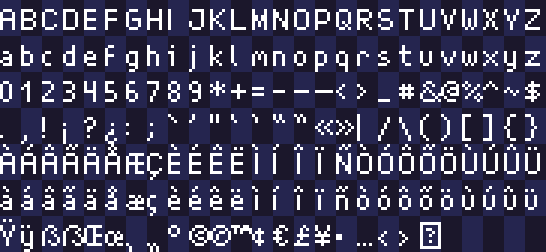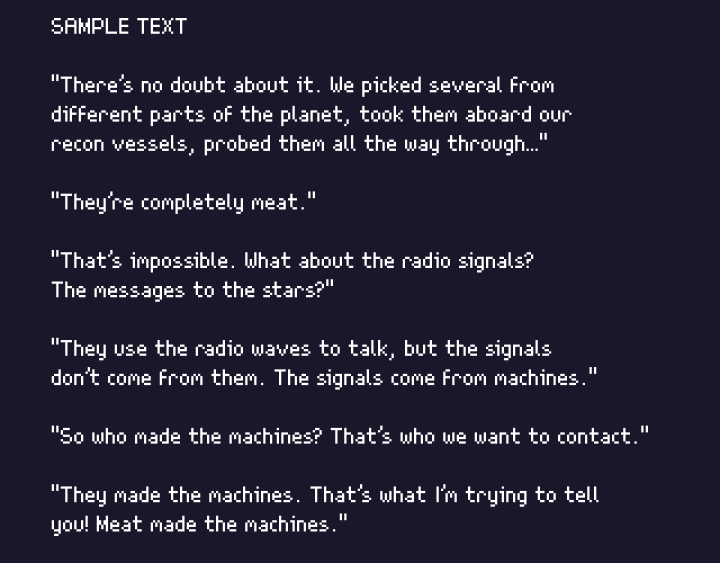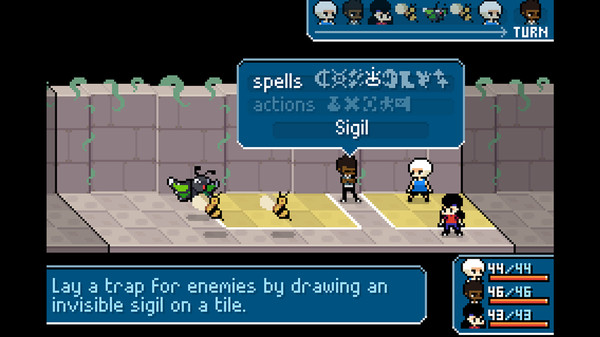
小巧简洁的Supersoft像素字体素材,专为像素艺术游戏而设计,易于阅读。这款字体可用于商业和非商业游戏、视频、直播叠加层、网站等等!
该字体支持以下所有字符:
像素字体与普通矢量字体不同,它们只能以一种尺寸显示,不能随意调整大小。因此,所有字体都已标准化为 16 号字。如果您需要将字体放大 2 倍 或 3 倍,可以使用 16 的倍数(例如 32、48、64 等)。